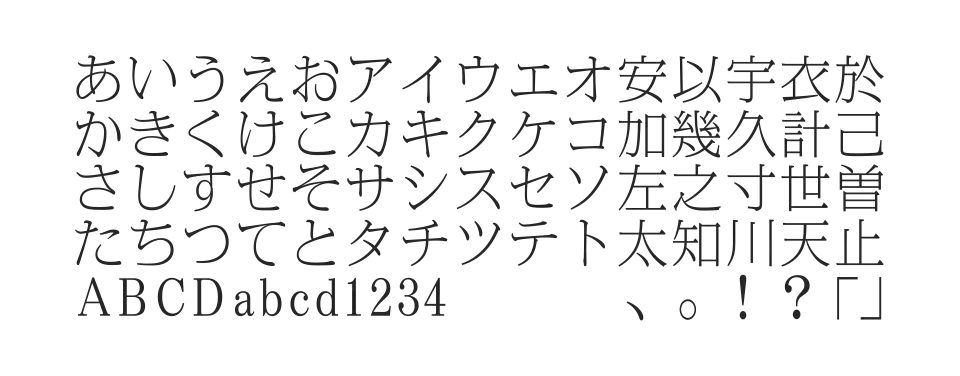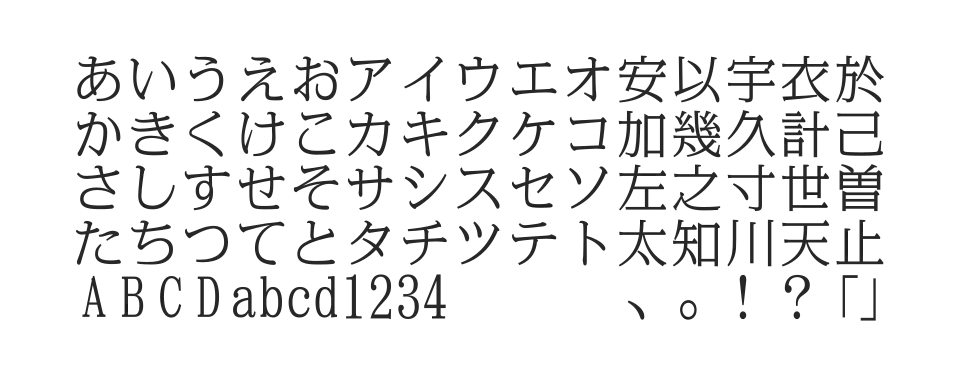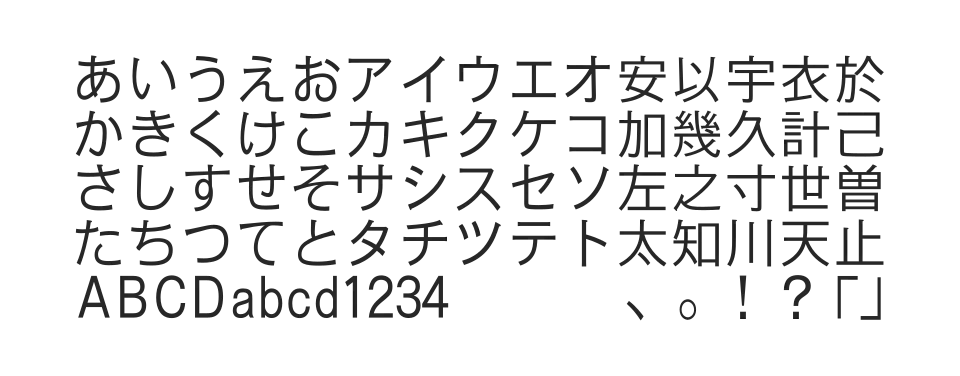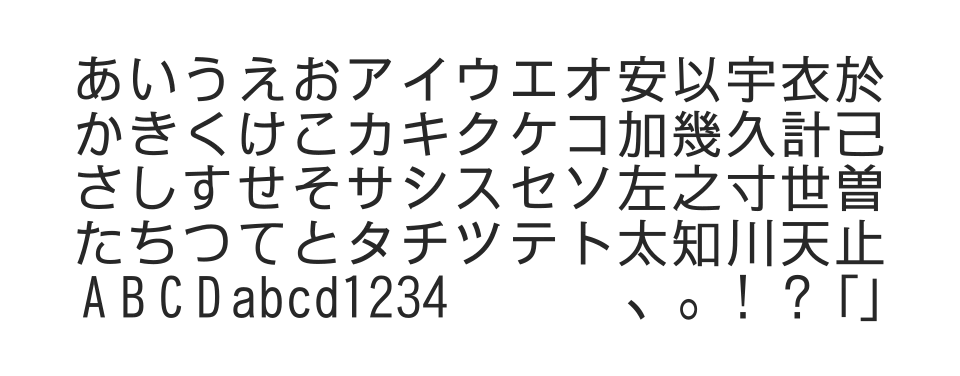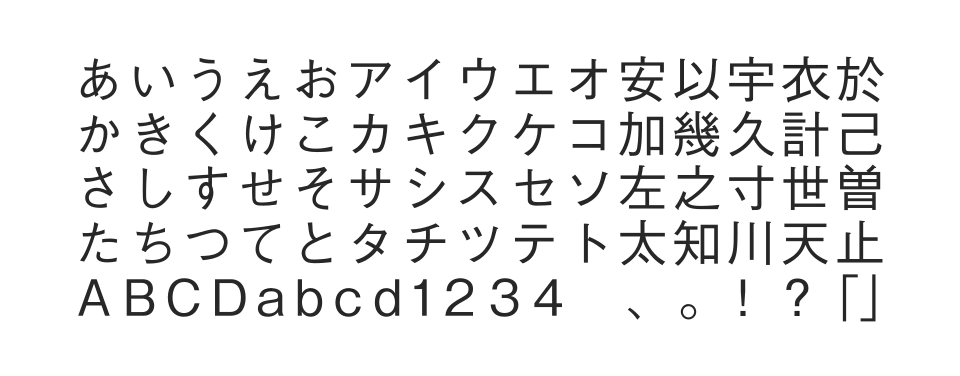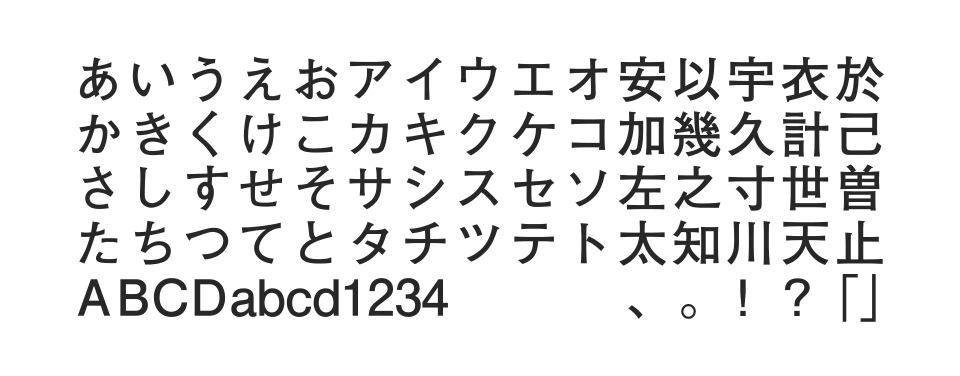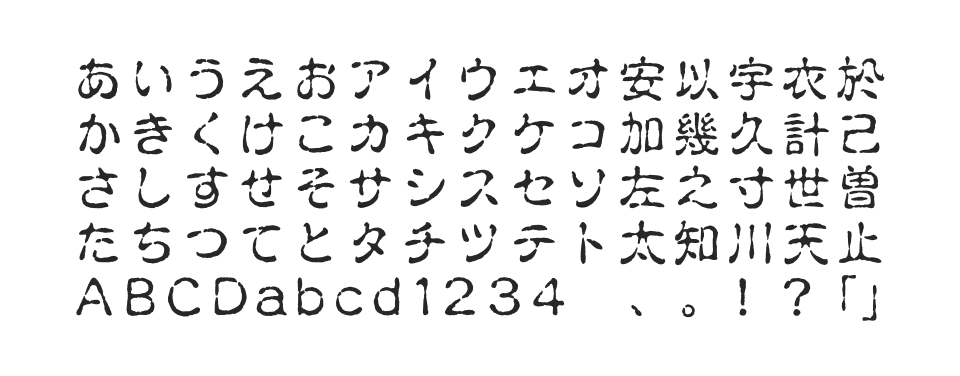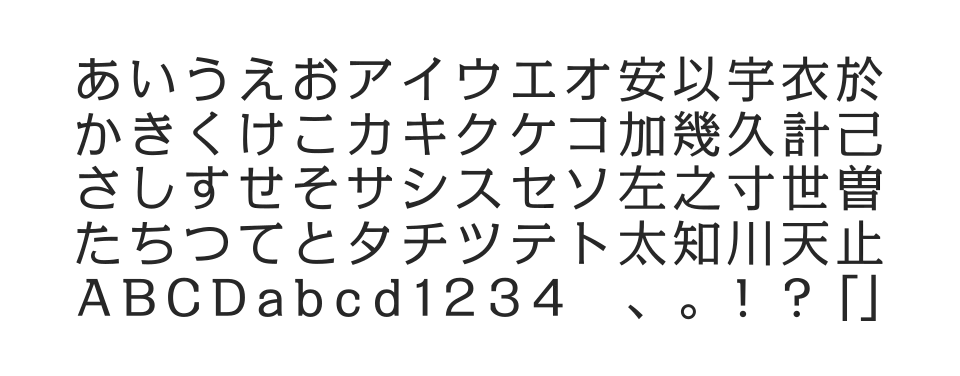
ゴシック体と明朝体の両方の特長をもった独特の書体。ゴシック体の縦画・横画の比率に明朝体のようなエレメントを採用し、小さなサイズでは読みやすく、大きなサイズではアクセントが際立ちます。
伝統的な古印体スタイルのフォント。筆文字の風合いを持つ和風デザインに最適な書体で、和食店の看板や伝統的な文書、賞状などの用途に幅広く使用されています。
活字書体のデザインを忠実に引き継ぐゴシック体。縦画には打ち込みのアクセントがあり、視認性を考慮した抑揚により小サイズでもくっきりと、大サイズでは力強く見せることができます。
日本語DTPにおけるモリサワ基本7書体の一つで、標準的な明朝体として広く使用されている。プロのDTPで定番の明朝体として、本文組みから見出しまで幅広い用途に対応します。
日本語DTPにおけるモリサワ基本7書体の一つで、スタンダードなゴシック体として幅広く使用。癖のない字体でどんなデザインにも合わせやすい万能型フォントです。
伝統的なゴシック体の流れを引き継ぐ風格あるゴシック体。しっかりとした骨格を備え、ハネやハライの先端まで力強さと流れを感じさせ、親しみやすく信頼感のある表情が特徴です。
エムニュースシリーズのゴシック体版。新聞・報道用途に特化して開発されたU-PRESS対応フォントで、エムニュースエムと組み合わせて使用できる専用ゴシック体です。
U-PRESS対応ゴシック体として開発されたフォント。報道関係での使用を目的とし、共同通信社の文字コードに対応した専用の文字セットを持つ新聞・メディア向けゴシック体です。
毎日新聞社が新聞本文組用に開発した明朝体。標準的な新聞明朝よりもしっかりと黒みがあり、フトコロや字面をやや控えて読みやすさを保つよう設計されている新しい大型文字です。
毎日新聞社が新聞本文組用に開発した明朝体。扁平前提で設計され、新聞印刷条件下に適合。大ぶりでクリアーな印象が特徴で客観的な文章に適用。